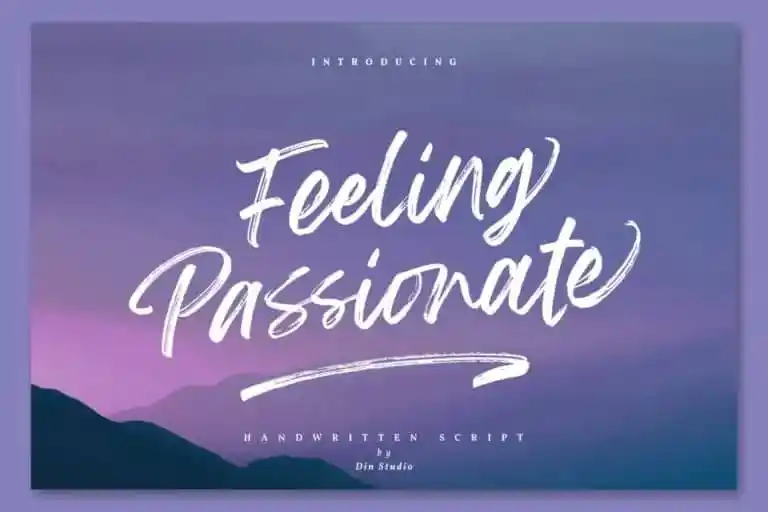
A Feeling Passionate Brush Font foi criada meticulosamente para adicionar uma sensação natural do handmade à sua tipografia, resultando em texto que aparece elegante, luxuoso e moderno. Ideal para designers que valorizam um toque autêntico em seus trabalhos de design, esta fonte oferece a oportunidade de criar texturas únicas e sofisticadas. Com uma personalização cuidadosa, ela se adapta perfeitamente aos projetos que exigem um ar de handmade, seja para criações digitais ou impressas. Esta font é o ideal para quem procura transpor suas ideias em um estilo autêntico e único. Perfecto para adicionar um toque distintivo a qualquer projeto gráfico, Feeling Passionate Brush Font é uma escolha inteligente tanto para iniciantes quanto para profissionais de design que valorizam a mão da criação na era digital.